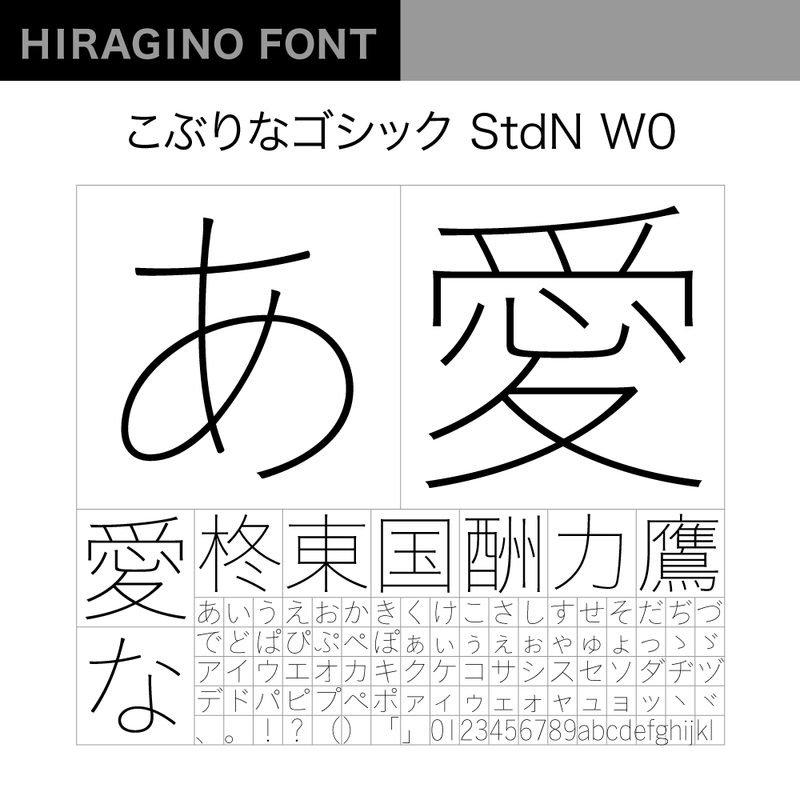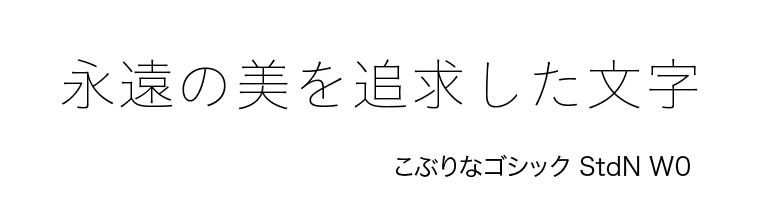
写真植字や活版を用い、エディトリアルを中心に本格組版を続けてきた職人たちの生の声を汲み上げ、それらに幅広く応えうるデザインに昇華させた、贅沢で、欲張りで、徹底的に玄人好みの書体です。漢字は「ヒラギノ角ゴ」をやや小さめに改刻、仮名は東京築地活版製造所の名作明朝を飜刻した「游築五号仮名」の骨格をゴシック化し、素直なエレメントから無用な鋭角を省きつつ丸味を持たせ、やわらかな風合いを感じさせるデザインに仕上げています。